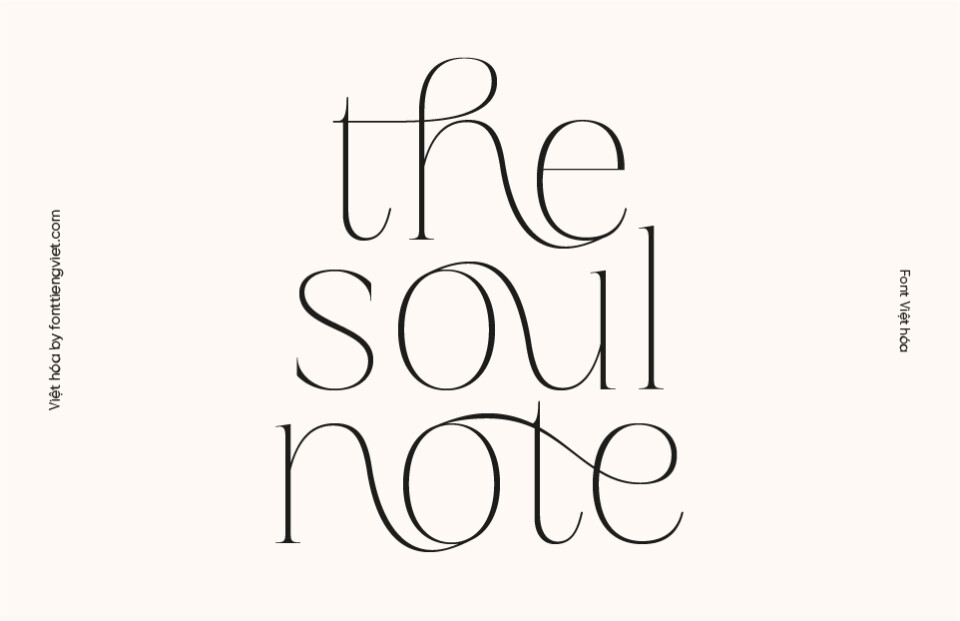
Font Việt hóa 1FTV VIP Soul Note Display
Font Việt hóa 1FTV VIP Soul Note Display – Sự Kết Hợp Hoàn Hảo Giữa Nghệ Thuật Và Sáng Tạo
Giới thiệu về Font Việt hóa 1FTV VIP Soul Note Display
Trong thế giới thiết kế đồ họa hiện đại, việc tìm kiếm một bộ font vừa mang tính thẩm mỹ cao, vừa đảm bảo tính ứng dụng linh hoạt luôn là ưu tiên hàng đầu của các designer. Font Việt hóa 1FTV VIP Soul Note Display chính là một lựa chọn xuất sắc như thế. Đây là bộ font được thiết kế với phong cách Display đầy ấn tượng, giúp tạo điểm nhấn mạnh mẽ cho mọi tác phẩm nghệ thuật. Khi sử dụng Font Miễn Phí để làm phong phú kho tài nguyên cá nhân, bạn sẽ nhận ra rằng Soul Note không chỉ đơn thuần là các ký tự mà còn là một ngôn ngữ hình ảnh đầy cảm xúc. Phiên bản Việt hóa này đã được tối ưu hóa hoàn toàn về dấu câu, giúp người dùng tại Việt Nam dễ dàng sử dụng trong các dự án chuyên nghiệp mà không lo lỗi hiển thị.
Đặc điểm nổi bật của Font Việt hóa 1FTV VIP Soul Note Display
Phong cách thiết kế độc bản và tinh tế
Điều làm nên sức hút của Font Việt hóa 1FTV VIP Soul Note Display chính là những đường nét uốn lượn mềm mại kết hợp với các góc cạnh sắc sảo. Bộ font này mang hơi hướng của sự tự do, giống như những nốt nhạc tâm hồn (Soul Note) được bay bổng trên mặt giấy. Các ký tự được chăm chút tỉ mỉ để tạo ra sự cân bằng thị giác tuyệt vời, phù hợp cho những ai muốn thể hiện cá tính riêng biệt. Đối với các bạn học sinh và sinh viên, đây là công cụ hữu ích để làm nổi bật các bài thuyết trình hoặc thiết kế bìa báo tường, giúp thông điệp truyền tải trở nên cuốn hút và dễ đi vào lòng người hơn bao giờ hết.
Khả năng ứng dụng linh hoạt trong nhiều lĩnh vực
Không chỉ giới hạn trong các thiết kế in ấn, Font Việt hóa 1FTV VIP Soul Note Display còn phát huy tối đa sức mạnh trong lĩnh vực kỹ thuật số. Bạn có thể sử dụng font chữ này cho tiêu đề website, banner quảng cáo, hoặc các bài đăng trên mạng xã hội như Facebook, Instagram để thu hút sự chú ý của người xem ngay từ cái nhìn đầu tiên. Đặc biệt, trong môi trường giáo dục, thầy cô có thể dùng bộ font này để trang trí các bảng tin nhà trường hoặc tài liệu giảng dạy, tạo nên một không gian học tập sáng tạo và thân thiện. Tính tương thích cao với các phần mềm đồ họa phổ biến như Photoshop, Illustrator hay Canva giúp quá trình thiết kế trở nên mượt mà và hiệu quả.
Cách tối ưu hóa Font Việt hóa 1FTV VIP Soul Note Display trong thiết kế
Lựa chọn màu sắc và bố cục phù hợp
Để Font Việt hóa 1FTV VIP Soul Note Display thực sự tỏa sáng, người thiết kế cần chú ý đến việc phối hợp màu sắc. Vì đây là một font dạng Display có độ tương phản cao, bạn nên ưu tiên sử dụng các gam màu đơn sắc hoặc gradient nhẹ nhàng để không làm rối mắt người nhìn. Về bố cục, hãy đặt font chữ này ở vị trí trung tâm hoặc những nơi cần tạo sự tập trung lớn nhất. Việc kết hợp Soul Note với các font chữ Sans-serif đơn giản khác sẽ tạo nên một sự đối lập thú vị, giúp tổng thể bản thiết kế trở nên chuyên nghiệp và có chiều sâu hơn. Đừng ngần ngại thử nghiệm các kích thước khác nhau để tìm ra tỷ lệ vàng cho tác phẩm của mình.
Kết luận về bộ Font Việt hóa 1FTV VIP Soul Note Display
Việc sở hữu một bộ font chất lượng như Font Việt hóa 1FTV VIP Soul Note Display sẽ giúp bạn tự tin hơn trong hành trình sáng tạo nội dung. Với sự tỉ mỉ trong từng đường nét và khả năng hỗ trợ tiếng Việt hoàn hảo, đây chắc chắn là người bạn đồng hành không thể thiếu cho các dự án thiết kế từ đơn giản đến phức tạp. Hãy truy cập ngay vào kho Font Miễn Phí, Font Việt Hóa, Font Việt hóa 1FTV VIP Soul Note Display để tải về và trải nghiệm sức mạnh của sự sáng tạo. Hy vọng rằng bộ font này sẽ giúp các bạn học sinh, giáo viên và những người yêu cái đẹp tại Việt Nam có thêm nhiều cảm hứng để tạo nên những sản phẩm ấn tượng, mang đậm dấu ấn cá nhân và đóng góp giá trị tích cực cho cộng đồng thiết kế.